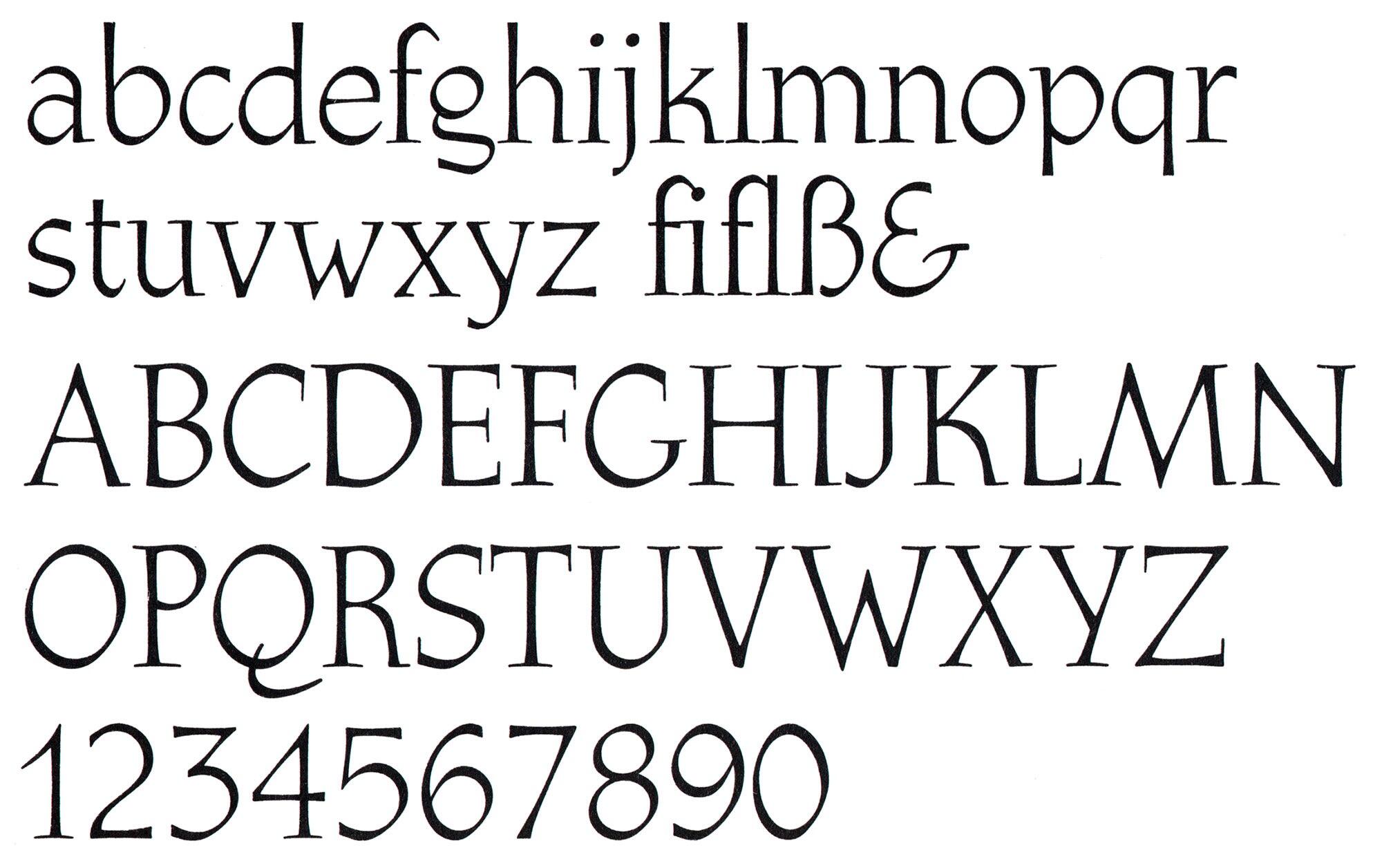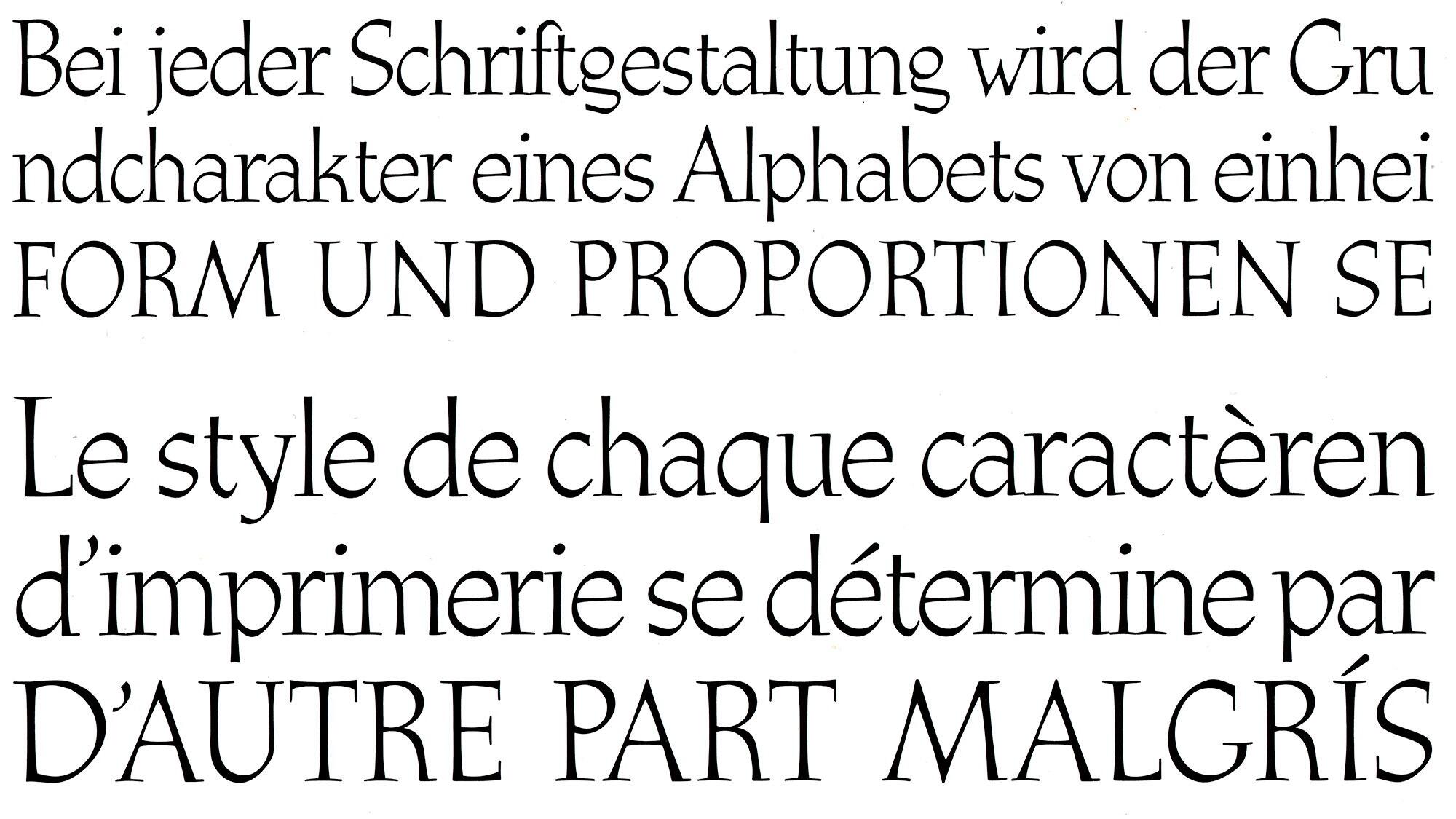
Font-Wiki: Athenaeum
Die Athenaeum ist eine Antiqua von Alessandro Butti mit kalligrafischem Duktus und erschien in den 1940er Jahren bei der italienischen Gießerei Nebiolo. Zur Familie gehören zwei Strichstärken, eine Kursive und zwei Sets von Initialen. Die Schrift war später auch für den Fotosatz erhältlich und ist heute digital in einer Pro-Version mit erweiterter lateinischer Belegung über Monotype verfügbar.